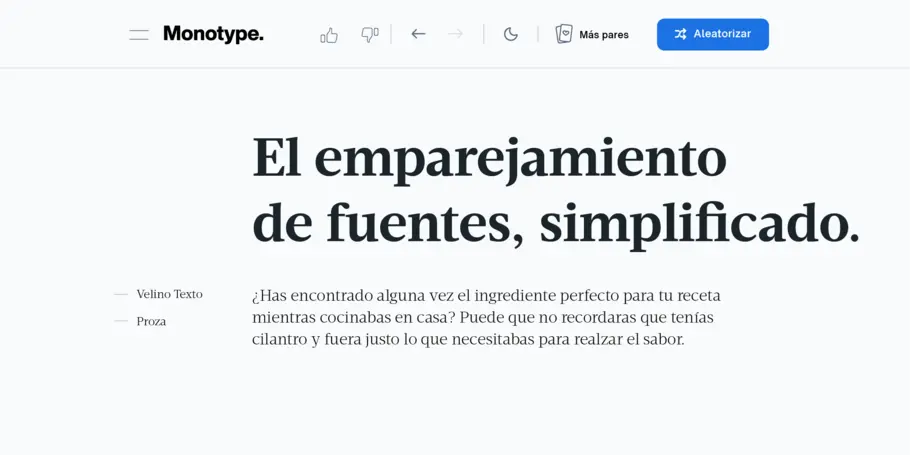
La IA en acción: El arte de emparejar tipos de letras.
« El par de tipos de letra ideal podría ser único para tu marca, con tu mensaje, y acorde a tus elecciones tipográficas. »
Terrance Weinzierl, director creativo de tipografía.
Se muestra el emparejamiento de fuentes de Monotype, combinando una fuente de remate y una letra de palo seco.
El emparejamiento de fuentes es una práctica subjetiva con infinitas posibilidades. Pero ¿y si contaras con una herramienta de IA que tuviera en cuenta tu experiencia y emociones como si fuera tu asistente personal?
¿Has encontrado alguna vez el ingrediente perfecto para tu receta mientras cocinabas en casa?
Puede que no recordaras que tenías cilantro, cacahuetes triturados o zumo de limón, y fuera justo lo que necesitabas para realzar el sabor. O quizás alguna vez has empezado a vestirte por la mañana y, tras elegir tus vaqueros favoritos, no tenías claro qué camiseta ponerte. Entonces, tuviste en cuenta tu estado de ánimo y el lugar al que ibas. Y finalmente, optaste por un jersey cálido. En ambos casos, creaste algo nuevo y distintivo, una experiencia mejorada. Y como resultado, te invadió una sensación de placer y satisfacción.
Esto es lo que se siente al encontrar el par de fuentes perfecto.
El motor de emparejamiento de Monotype con IA.
Estos son ejemplos de decisiones diarias que tomas sobre armonía y contraste.
Estas combinaciones son diseños cuidadosamente seleccionados.
Como con cualquier combinación, es una práctica subjetiva con infinitas posibilidades. Hay muchas opciones buenas, algunas malas y unas pocas excepcionales.
Ahora imagina si contaras con una herramienta de IA que tuviera en cuenta tu experiencia y emociones como si fuera tu asistente personal. Podría ofrecer ideas increíbles, además de mejorar la rapidez y calidad de tus decisiones creativas. Estas sugerencias incluso podrían funcionar como orientación o fuente de inspiración. Estamos aprovechando la IA para ampliar y diversificar nuestras sugerencias de emparejamiento de fuentes.
El poder del emparejamiento de fuentes.
Imaginemos que estás diseñando una revista. Lo ideal sería contar con una paleta tipográfica flexible, con un tipo de letra con remate y otra de palo seco que funcionen bien para el cuerpo del texto. En un artículo se podría usar la letra de palo seco en el cuerpo y en el siguiente, la letra con remate. Un par eficaz como este podría proporcionar diversidad dentro de la uniformidad.
Emparejar tipos de letras amplía la paleta tipográfica, ya que ofrece más opciones de jerarquía, textura y peso, así como la oportunidad de ajustar el tono. Por ejemplo, la pieza clave de una familia de tipos de letras de palo seco podría ser una opción que responda bien a la mayoría de las necesidades tipográficas de una marca. No obstante, podría ofrecer un aspecto más cercano si la combinaras con otra de palo seco redondeada, o un aspecto más relajado y personal si la combinas con una de estilo manuscrita; e incluso podría adoptar un tono más sofisticado y serio si la combinas con un tipo de letra con remate. Al encontrar un par único de tipos de letras, puedes transformar la elección principal en algo más inusual y especial.
Algunas marcas y proyectos pueden permitirse usar solo una familia de tipos de letras; pero una segunda opción puede aportar mucha flexibilidad y riqueza a los mensajes. También puede ser una manera de ampliar o renovar una marca existente. Quizás una marca consolidada se expande agregando otro producto o servicio que necesita un tono diferente, pero que podría beneficiarse de las similitudes visuales con la marca principal… Este sería el caso perfecto para recurrir al emparejamiento de fuentes.
Los pares de fuentes son sumamente valiosos: ofrecen variedad, aportan funcionalidad y ayudan a definir el tono, de forma que pueden impulsar marcas nuevas o revitalizar marcas consolidadas.
Cómo emparejar fuentes: de la armonía al contraste.
Hay parejas de fuentes de toda clase, desde las armoniosas hasta las que contrastan. Dos elementos son armoniosos cuando tienen un aspecto similar, combinan bien o sus cualidades formales guardan relación. Un ejemplo de armonía sería combinar una camisa azul y unos vaqueros azules de un tono ligeramente distinto. Si dichos vaqueros se combinaran con una camisa naranja, el contraste sería mucho mayor. Recurrir al contraste implica resaltar las diferencias.
Por lo general, emparejar una letra de palo seco con otra de palo seco apenas genera distinción; de hecho, presenta demasiada armonía y escaso contraste. En lugar de esto, para que tu paleta tipográfica sea más sofisticada, combina una letra de palo seco con una letra con remate. Por ejemplo, una camisa azul con unos vaqueros azules podría verse muy apagada, ya que presenta una excesiva armonía, pero una camiseta naranja podría presentar demasiado contraste. En tal caso, lo mejor sería buscar un término medio y elegir un color análogo, como el verde o el violeta, que están cerca del azul en el círculo cromático. Esto ofrece un ligero contraste dentro de una considerable armonía. En este sentido, la gama de parejas de tipos de letras funciona de manera similar a un círculo cromático.
Los pares de tipos de letras pueden guardar una gran armonía, especialmente si ambas son estilos de una misma familia; por ejemplo, Helvetica Now Regular y Bold. Combinan bien porque tienen un aspecto similar, con una estructura y proporciones parecidas, al tiempo que ofrecen un ligero contraste, necesario para establecer una jerarquía en cualquier diseño. En resumen, cada familia está diseñada para que sus tipos de letras se puedan emparejar entre sí, por eso se incluyen tantos pesos distintos. Las «superfamilias», como FF DIN, Kairos o Macklin, tienen muchos estilos relacionados que son fáciles de emparejar, como un tipo de letra de palo seco, uno con remate o un «stencil». Los pares predefinidos son fáciles de elegir, ya que el nombre de la familia indica que los tipos de letras están relacionadas.
Esta herramienta proporciona inspiración e información sobre el arte de emparejar fuentes, y te permite formar pares de mayor calidad y de forma más rápida. No es una cuestión de casualidad. Es resultado del trabajo y de combinar tipografía, tecnología y experiencia con solo pulsar un botón.